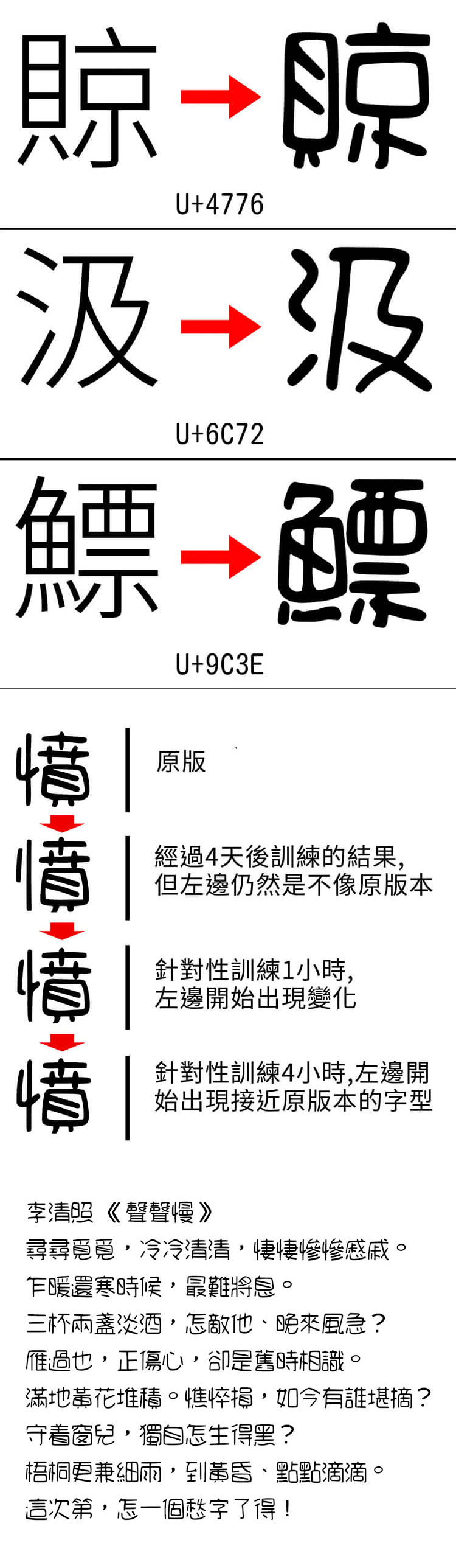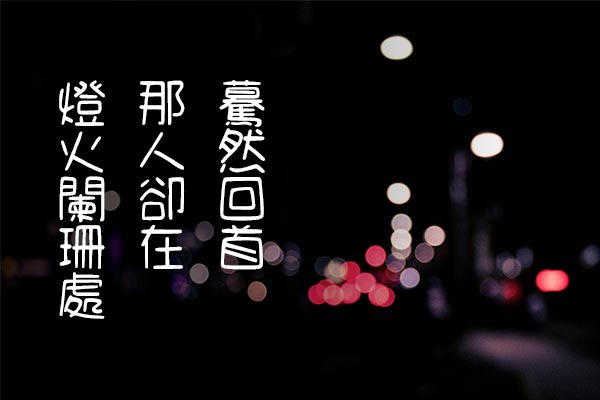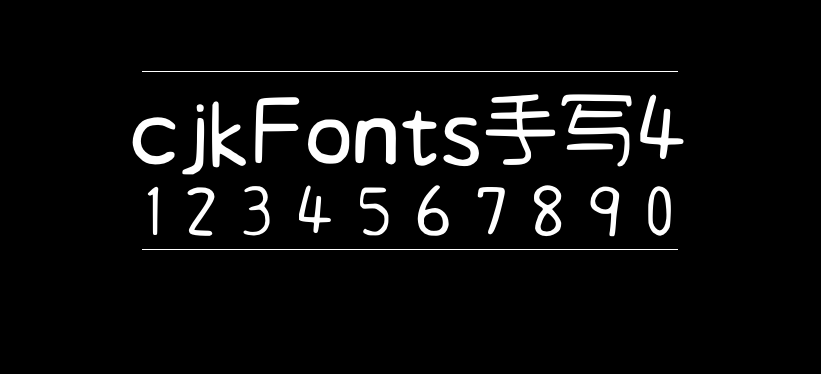
cjkFonts手写4
cjkFonts手写4(cjkFonts 手寫4 、 cjkFontsHandwriting4)是基于“清松手写体4”通过AI深度学习造字形成的更全的字体,原本清松手写体4大约有四千多字,现补齐至约1万2千字,基本上繁体基本不缺字,简体常用字也已经覆盖,更多生僻字形待有时间才再加入。
由于是电脑学习了字型的特点及风格后,每个字根据学习后的数据造字,所以字体的风格会跟清松手写体4有细微的区别。
这次是1万2千字的版本,大约用了2个月时间完成制作。清松手写体4的风格跟一般字变化比较大,在整过训练过程中,要反复检视结果,然后再训练,再检视,直至大部份的字型跟原版接近才能开始后期制作。